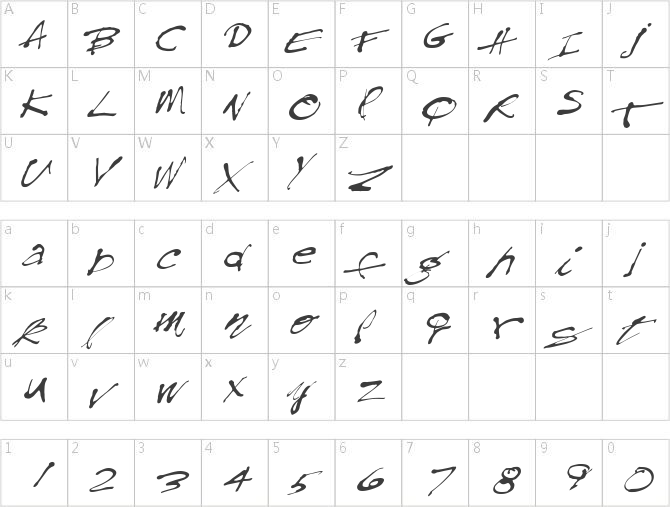
FZ HAND 28 ITALIC 詳情頁
FZ HAND 28 ITALIC
FZ HAND 28 ITALIC字體字庫是一款讓人賞心悅目、百看不厭的英文字體,適合各類廣告和產(chǎn)品包裝設(shè)計應(yīng)用,字體大小0.08MB,格式為ttf字體,上傳用戶是青檸檬,作者/版權(quán)方為未知